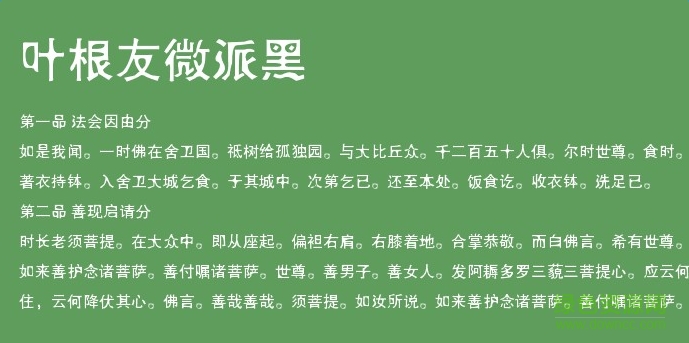
葉根友微派黑
葉根友微派黑字體是一款水流創(chuàng)意風(fēng)格字體軟件,微派黑體是葉根友字體系列中藝術(shù)氣息十足的一款字體,字體筆畫形如流水,融入波浪形狀,非常好看,還有更多好看字體歡迎來綠色資源網(wǎng)下載體驗(yàn)!
葉根友微派黑字體是一款正文標(biāo)題字體,適用于時(shí)尚品牌設(shè)計(jì)和內(nèi)容簡(jiǎn)介,其獨(dú)特的波浪藝術(shù)風(fēng)格別具特色!
葉根友微派黑字體
該字體筆畫粗細(xì)不盡相同,偶爾的粗細(xì)間明,突出波浪的藝術(shù)美,非常好看,整體效果有點(diǎn)繁體的味道!